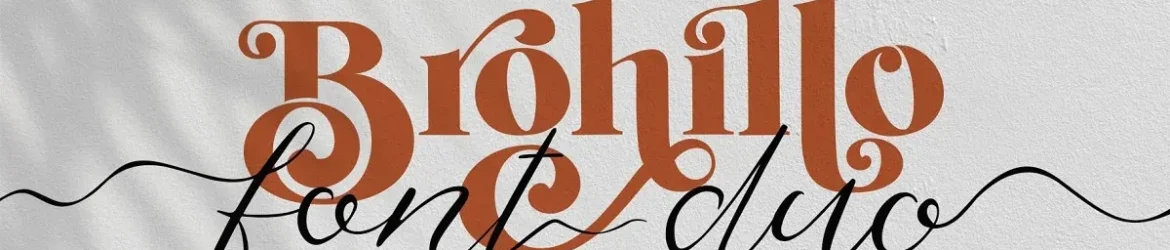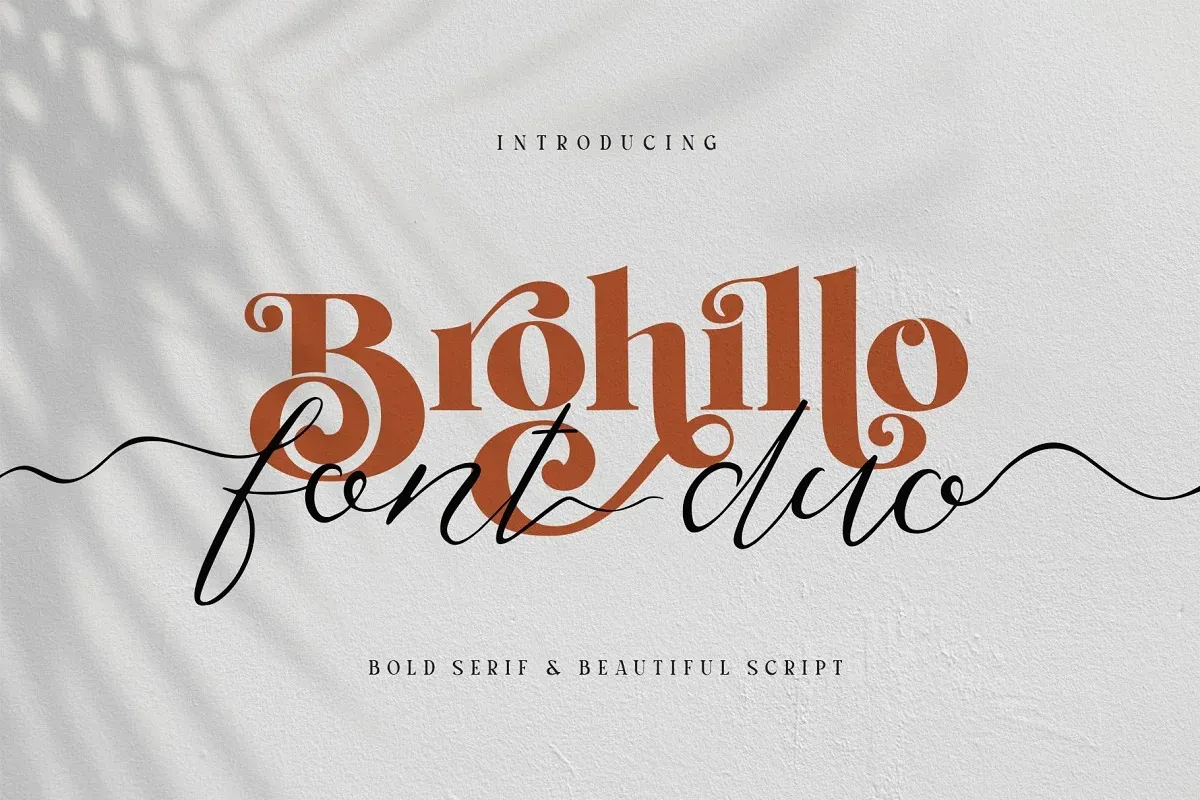
Brohillo Font
A Brohilio Font é uma elegante tipografia serif que carrega a riqueza de um estilo retro, inspirado na forma das pétalas de flores e curvas belas para formar sua estrutura. Esta fonte traz elementos românticos à qualquer design, sendo perfeita para aplicações com temas como casamentos, cartões de aniversário de Valentine, declarações românticas e mais. Com seu conceito elegante e poderoso, a Brohilio Font transforma simples ideias em trabalhos artísticos memoráveis, destacando-se não apenas pelo seu visual distintivo, mas também pela sua capacidade singular de transmitir sensibilidade e delicadeza através do texto.